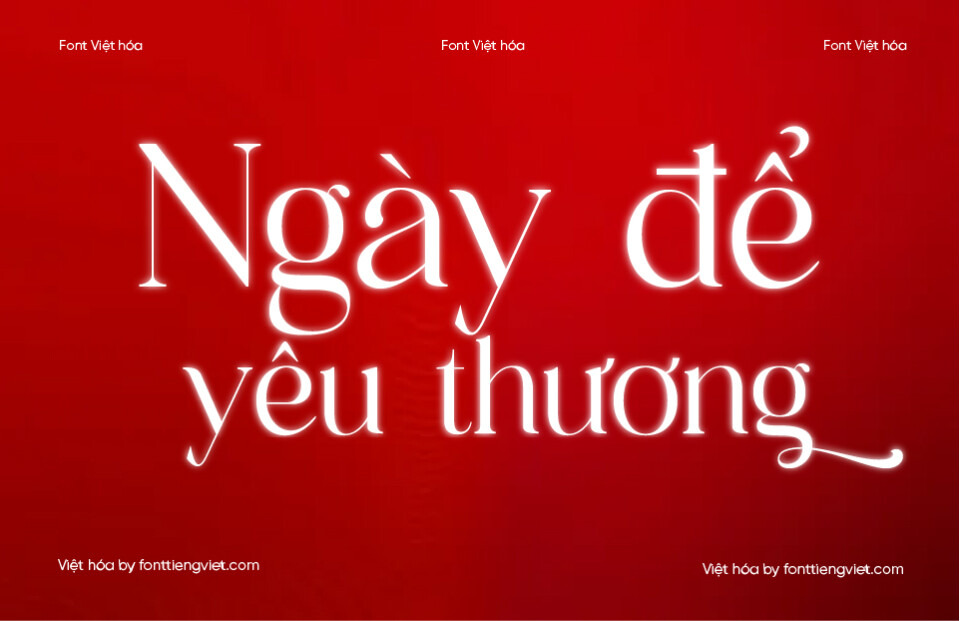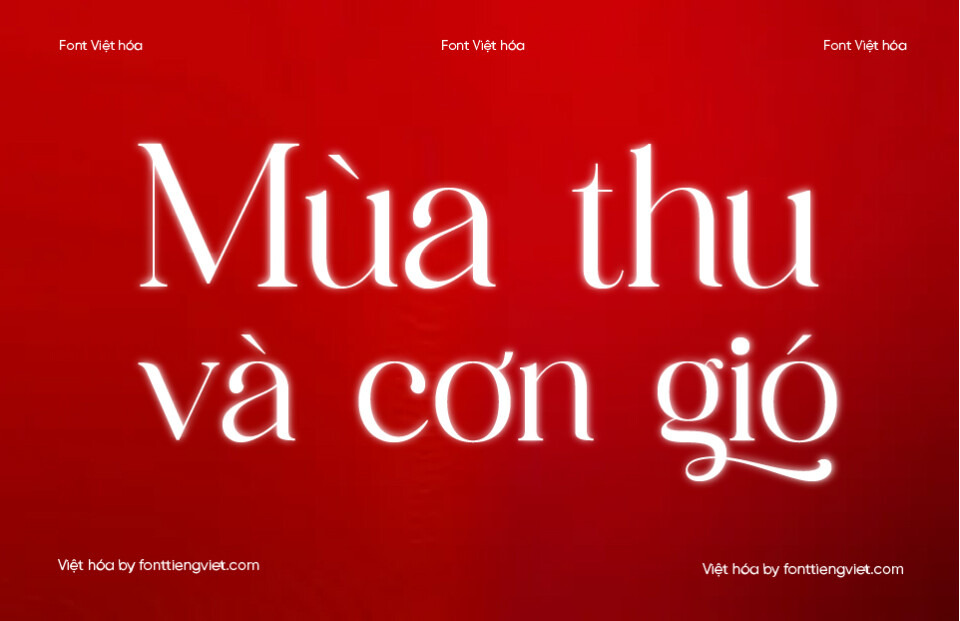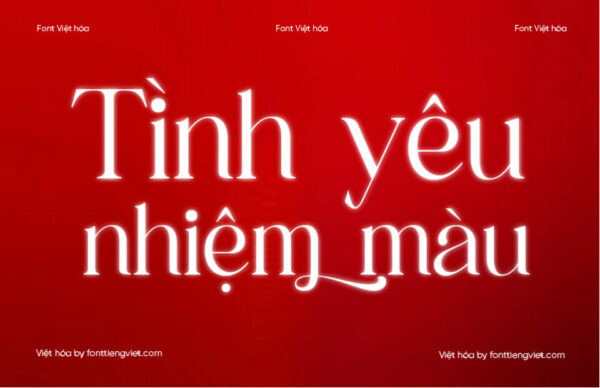
1FTV VIP Quahon là font chữ có chân được thiết kế với phong cách quý phái, mềm mại và đầy tinh tế, rất phù hợp cho các thương hiệu trong lĩnh vực spa, làm đẹp, trang sức và thời trang cao cấp. Font được Việt hóa hoàn chỉnh, mang đến trải nghiệm thiết kế chuẩn mực cho người dùng Việt.
Thanh lịch – Nghệ thuật – Ấn tượng
Tương tự như Billing Lottre, Quahon sở hữu những đường cong nhẹ nhàng và nhấn nhá thanh mảnh tạo cảm giác sang trọng mà không cầu kỳ, dễ dàng truyền tải thông điệp về sự đẳng cấp trong các thiết kế như:
Logo và nhận diện thương hiệu spa, thẩm mỹ viện
Ấn phẩm quảng bá trang sức, mỹ phẩm cao cấp
Thiệp mời, bao bì sản phẩm hoặc website thương hiệu
Poster sự kiện thời trang và làm đẹp
Việt hóa đầy đủ – Chuẩn từng chi tiết
Bộ font Quahon đã được Việt hóa chỉn chu, hỗ trợ tiếng Việt hoàn toàn với đầy đủ dấu và ký tự cần thiết. Giữ nguyên vẻ đẹp của từng chữ cái, không phá vỡ bố cục thẩm mỹ vốn có.
Phù hợp cho thiết kế cao cấp
Với khả năng thể hiện sự nữ tính, tinh tế nhưng vẫn chuyên nghiệp, 1FTV VIP Quahon là lựa chọn tuyệt vời để tạo nên những thiết kế có chiều sâu thẩm mỹ và đậm chất thương hiệu.
Font Việt hóa 1FTV VIP Quahon – Font chữ có chân sang trọng cho thiết kế làm đẹp và trang sức